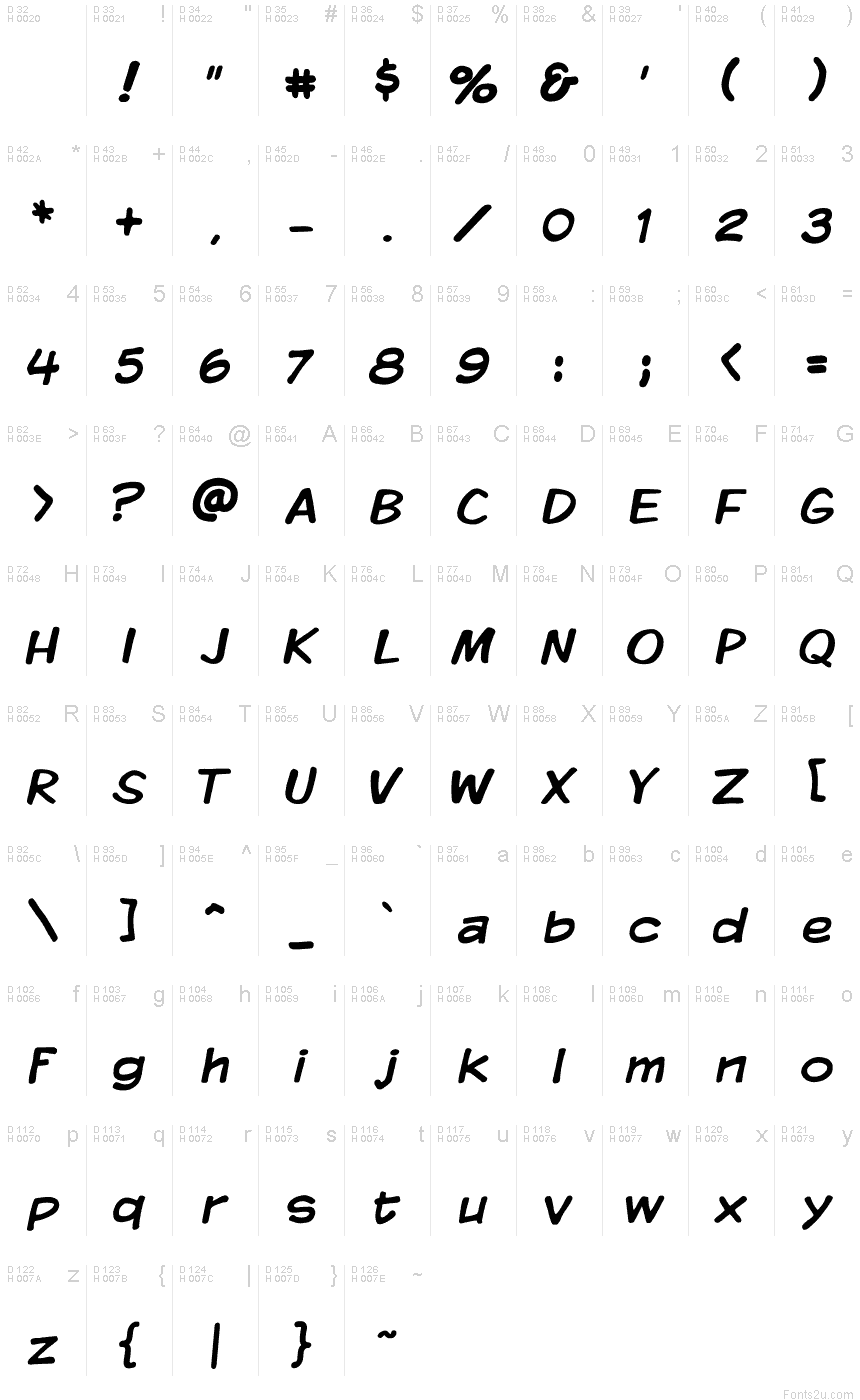
Komika Display od Wolfbainx & Apostrophic Labs to darmowy krój pisma w komiksowym stylu. Jego wyraziste, lekko pochylone litery wyglądają jak narysowane grubym markerem, z atramentowymi krzywiznami i miękkim, wibrującym charakterem, który jest żywy, a zarazem czytelny. Dzięki dużym, przyjaznym odstępom dymki, pointy i krótkie nagłówki wyróżniają się, nie sprawiając wrażenia niechlujnych czy stłoczonych.
Korzystając z Komika Display, nadasz natychmiast komiksowej energii swoim webkomiksom, żartobliwym panelom, plakatom na imprezy dla dzieci, zabawnemu brandingowi, miniaturkom na YouTube oraz naklejkom czy gadżetom. Ten darmowy font błyszczy użyty w dużym formacie i pogrubieniu, wsparty czystym krojem bezszeryfowym w podpisach lub dłuższych tekstach. Wnosi ten ręcznie kreślony, kreskówkowy klimat wszędzie tam, gdzie potrzebujesz wyrazistych i czytelnych liter.
Komika Display